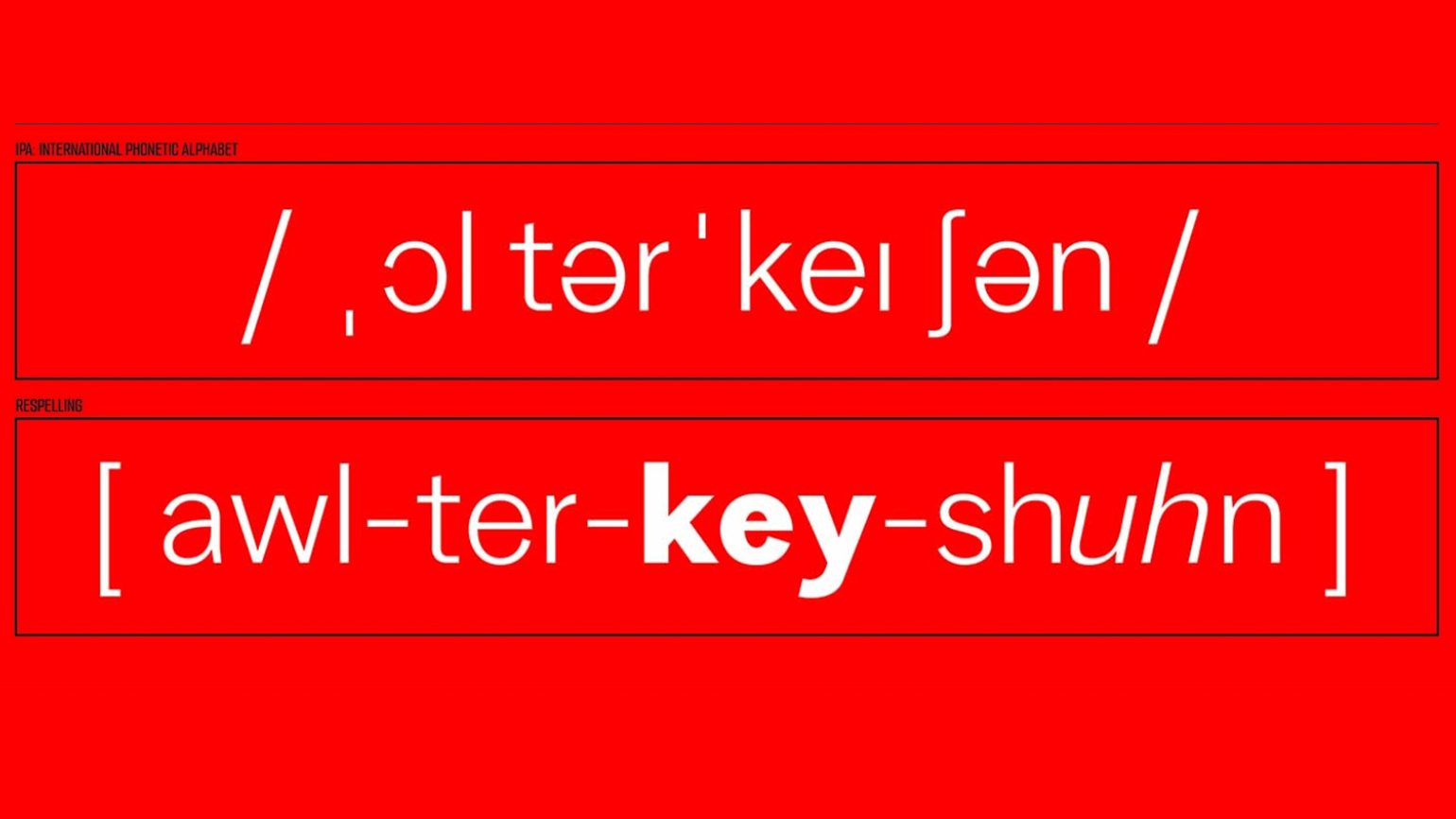
Студент из Таиланда создал шрифт, который помогает осваивать английское произношение
Чалемпол Джиттагасем сам испытывал сложности при изучении языка.
Аспирант факультета дизайна Государственного университета Сан-Франциско разработал шрифт, который должен помочь в изучении английского языка. Чалемпол Джиттагасем назвал его Vaja, что в переводе с тайского означает «Речь». Форма букв даёт небольшие подсказки о том, как правильно их произносить.
По словам Чалемпола Джиттагасема, он сам с трудом выучил английский язык, так как понятия не имел, сколько слогов в таких словах, как half или basically, и куда нужно ставить ударение. Он создал Vaja в рамках программы Type West от Letterform Archive, но первая концепция родилась, ещё когда он учился в магистратуре. Его дипломный проект был посвящён шрифтовому дизайну.
Шрифт Чалемпола Джиттагасема привлёк внимание старейшей профессиональной ассоциации дизайнеров в стране. Vaja был включён в список STA 100 — ежегодного конкурса Общества типографского искусства (STA), в рамках которого отмечают проекты инновационного коммуникационного дизайна со всего мира.
Изначальной идеей дипломной работы было создать шрифт, который должен был помогать с изучением английского именно тайцам, но в процессе Vaja стал инструментом для всех, кто осваивает этот язык. Автор создал курсив, а также версии насыщенности Bold и Thin, и каждое начертание работает как сигнальная система: например, жирное начертание указывает, где ставить ударение, курсив — где смягчать звук.
Vaja ещё нет в открытом доступе, но Чалемпол Джиттагасем надеется, что его будут использовать в словарях, академической литературе и даже в газетах.